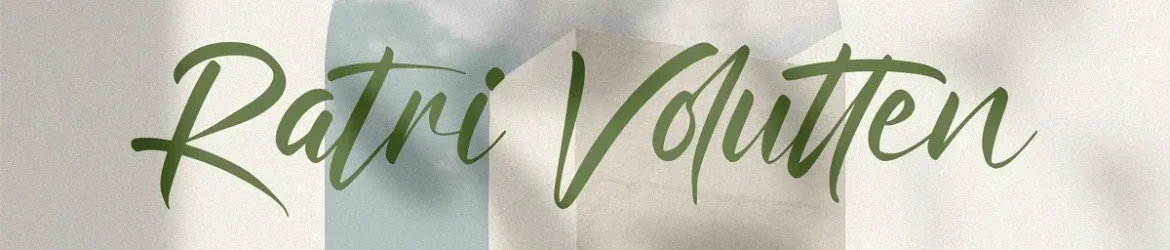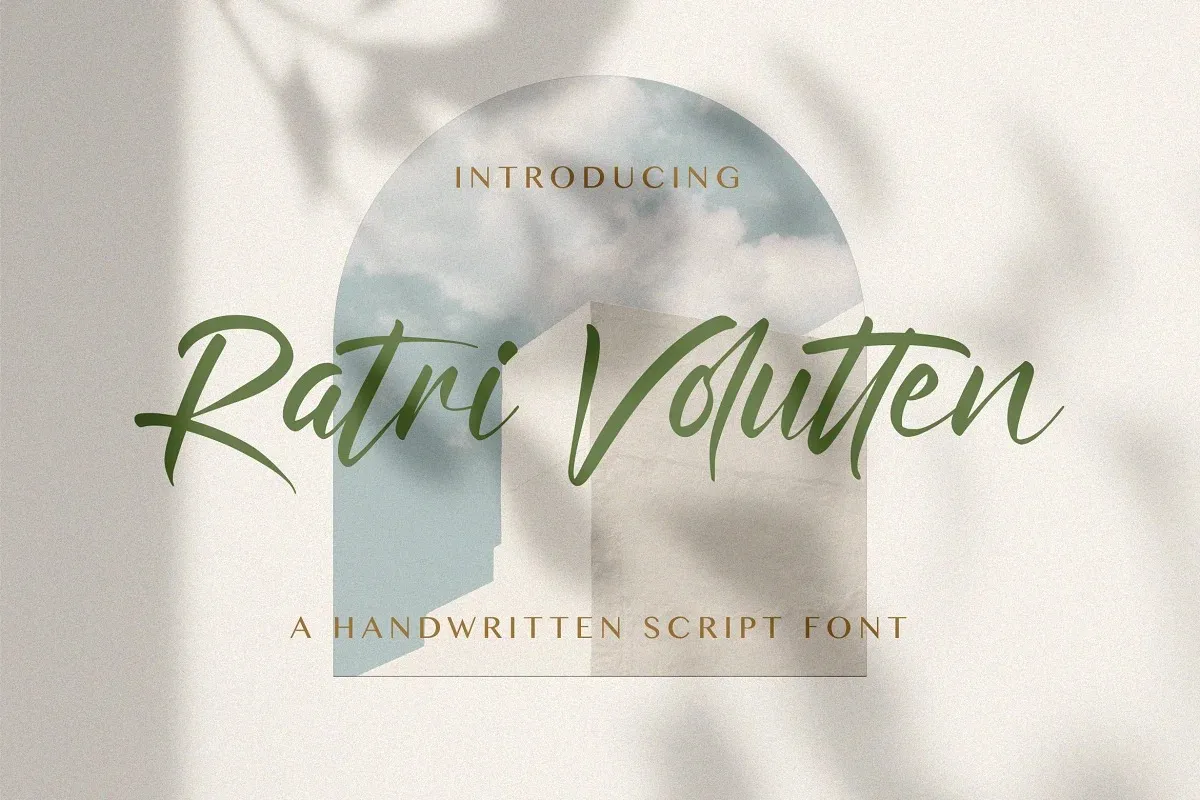
Ratri Volutten Font – Fonte Grátis
Ratri Volutten Font
A Ratra Volutten Font é uma elegante tipografia script que transmite sofisticação e estilo através de sua chamada para a arte com linha variável, criando um design arredondado e envolvente. Essa fonte vem do coração da arte do desenho à mão, trazendo consigo linhas sutis e harmoniosas que contribuem para um conjunto de caracteres bem equilibrados. Ideal para quem busca uma solução visual única e sofisticada, a Ratra Volutten Font se destaca no mercado dos fontes scripts. Adicionar esta fonte aos seus projetos mais criativos, você notará como ela transforma seus ideais em algo realmente vivo e vibrante. Com sua proposta de uso vasto e seu design refinado, a Ratra Volutten é uma escolha inteligente para criar designs únicos.